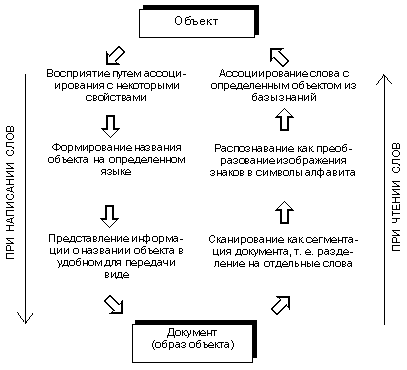
Шрифт - материальный носитель информации
4.1. Цифровые шрифты 4. Роль шрифта в наборном деле в процессе кругового преобразования текстовой информации о объекта к его образу и обратно видна из нижеприведенной схемы.
Приведенная схема (см. также схему принципов классификации шрифтов
Классификация шрифтов в зависимости от области применения, историческая классификация, а также классификация в соответствии со стандартами ГОСТ 3489 1-71 и ГОСТ 3489-38-72б используется в традиционном наборе. Она имеет место при рассмотрении ручного, строко- и буквоотливного, а также фотонабора и в настоящем пособии не рассматривается. В связи с внедрением вычислительной техники в процессы обработки информации появились новые возможности шрифтового оформления продукции. Средствами электронных преобразований легко получить из обычного шрифта непосредственно в процессе набора целый ассортимент его разновидностей: контурные, оттененные, заполненные орнаментом, деформированные и др. Кроме этого, появились специальные программы - шрифтовые редакторы для создания новых и редактирования существующих шрифтов. Появились и новые принципы классификации шрифтов, созданных электронным способом и существующих в памяти устройств в дискретной форме. Шрифт, как самостоятельный художественный и технический элемент, возник, по мнению специалистов, в связи с технологическим отделением процесса изготовления носителя изображе ия (ассортимента знаков определенного гарнитуро-кегленачертания или фонта) от процесса печати (воспроизведения этого изображения на бумаге). В современных системах допечатной обработки изданий публикации готовятся в цифровой форме, начиная от исходного материала до оригинала-макета. Для этого применяют самые современные технологии: оптическое распознавание текста, цифровую обработку изображений, автоматизированную проверку орфографии, компьютерную верстку, электронную почту, вывод на лазерные принтеры, ризографы, фотовыводные установки и т. д.